הפונטים שאנו בוחרים להשתמש בהם בעיצובים שלנו משפיעים בצורה משמעותית על המראה הכללי של התוצרים שלנו, בין אם מדובר במסמך וורד, מצגת, מודעת רחוב, או אפילו פוסט ברשתות החברתיות. האמנות של עיצוב הטקסט מעניקה לנו כלים רבים על ידם נוכל להתאים אישית את הטקסט שלנו ולהעביר את המסר בצורה יעילה יותר. אחד הכלים החשובים ביותר בעיצוב הוא הבחירה בפונט המתאים. במאמר זה נלמד איך מורידים פונטים בעברית ומתקינים אותם במחשב ובטלפון שלנו.
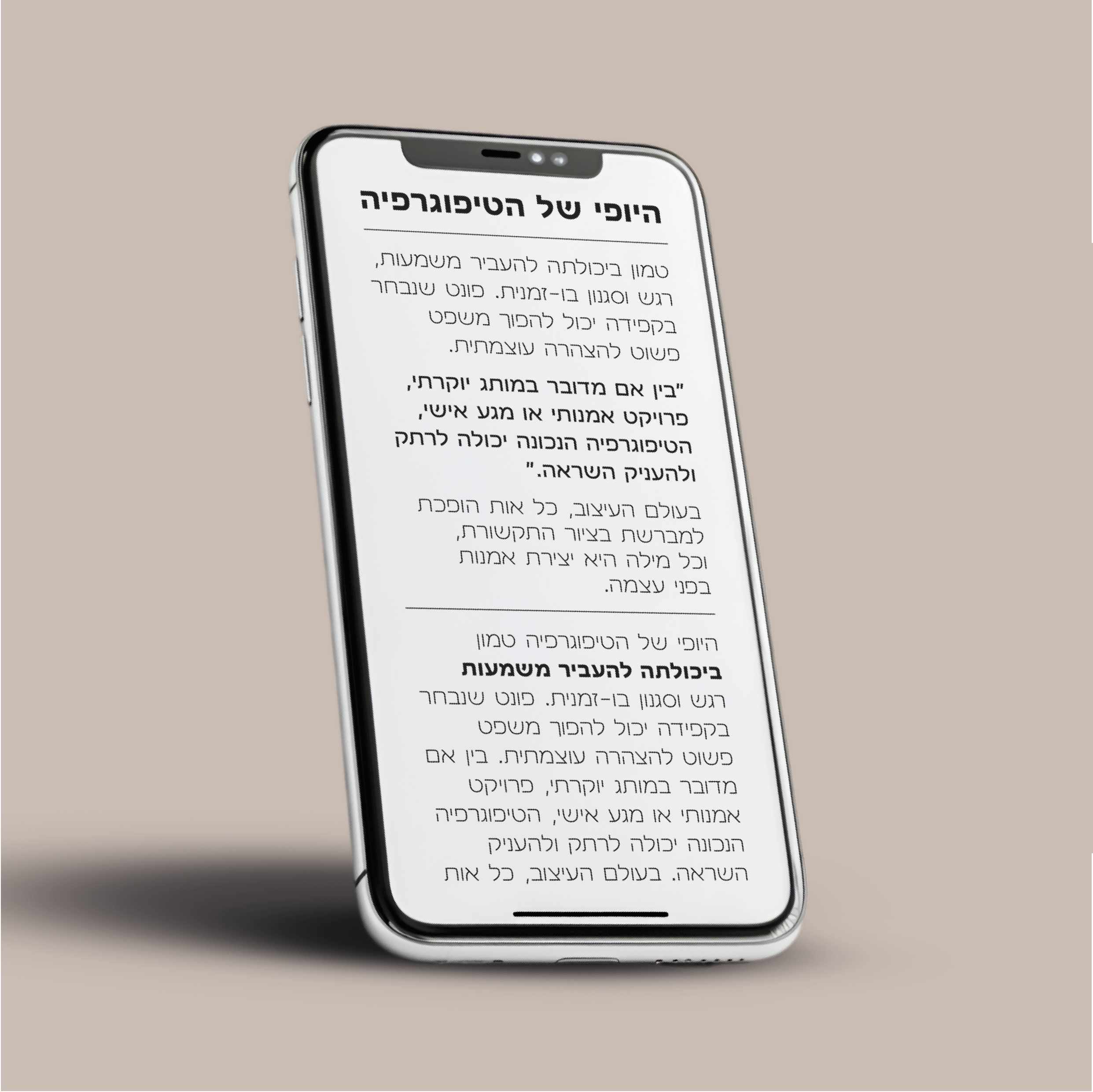
בחרו פונט שמתאים לסגנון המסמך שלכם. למשל, פונט אלגנטי יתאים להזמנה לחתונה, בעוד שפונט מודרני יתאים למצגת עסקית, כתב בלון יתאים למודעה גדולה ביום הולדת לילדים.
בחרו פונט קל לקריאה ומתאים לקהל היעד שלכם. כתב קטן ומסולסל במיוחד ככל הנראה לא יקל על הקריאה של הקהל המבוגר. נסו להקל על הקוראים כמה שיותר ולהפוך את הקריאה לנעימה עבורם.
שימוש במספר רב של פונטים באותו מסמך עלול ליצור עיצוב רועש ומבלבל, ולגרום לקורא לעזוב בטרם סיים את הקריאה.
לסיכום, הורדת פונטים חדשים היא דרך מצוינת להתאים אישית את המסמכים שלכם ולהעניק להם מראה ייחודי. טיפוגרפיה – אמנות העיצוב של הטקסט, מעניקה לכם כלים רבים להתאים אישית את הטקסט שלכם ולהעביר את המסר בצורה יעילה יותר על ידי בחירת הפונטים המתאימים. כך תוכלו לשפר משמעותית את האסתטיקה והקריאות של הטקסט שלכם.